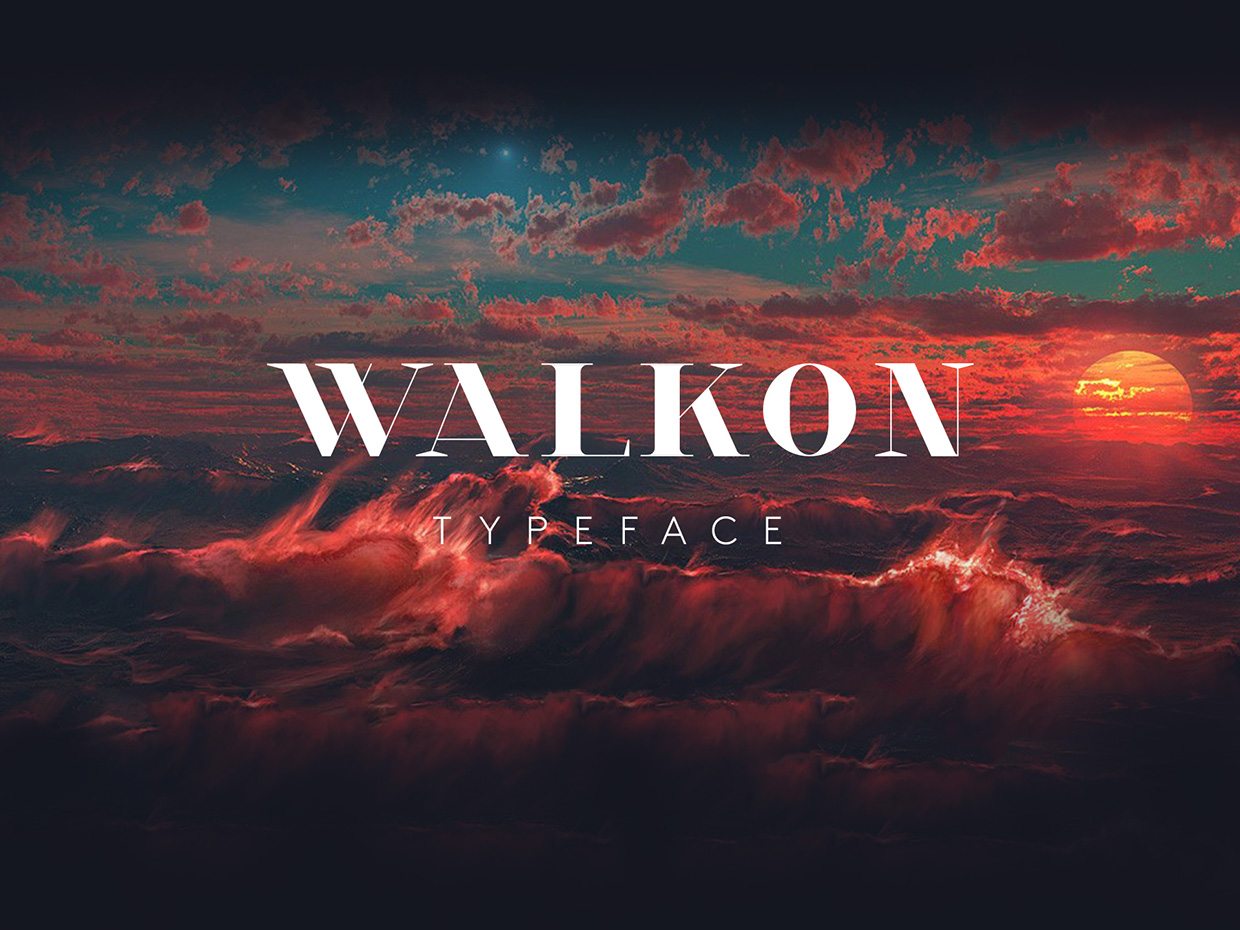
Font del giorno: Walk On Decò / Contemporaneo / Minimalista
il font che vi presentiamo oggi é: Walk On
Progettato nel cosi detto porto profumoato, a Hong Kong dal creativo Hanson Chan, Walk On è un tipo di carattere a stampo fusion  retrò e aggraziato in maniera Art Deco ma con un approccio contemporaneo piu minimalista, originariamente progettato come un tipo di carattere aziendale per il marchio di moda Wang & Lynch, è ora disponibile per il download gratuito.
Forme semplici e strutture ornamentali ridotti, WalkOn è particolarmente adatto per i titoli, ma può anche essere utilizzato per scopi  editoriali grazie alla sua vasta serie di lettere e caratteri  alternativi ivi compresi i numeri. il font è free sia per uso personale che commerciale. tuttavia perché il buon karma vi assista anche in futuro potete pensare di fare una piccola donazione al creatore del font 😉